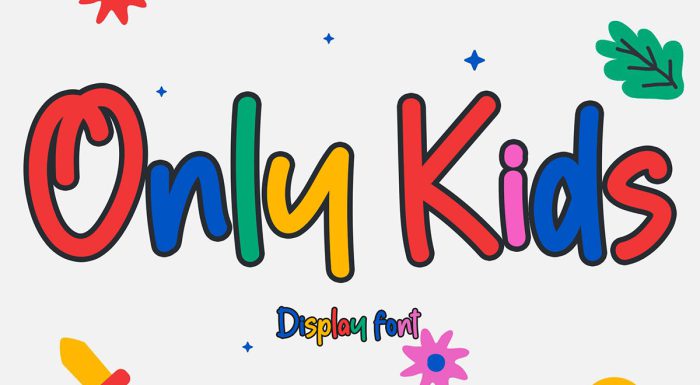
فونت Only Kids انگلیسی
| ⭐ توضیحات | فونت Only Kids Font را معرفی می کنیم، یک تایپ نمایشی بازیگوش و غریب که جوهره شادی و تخیل دوران کودکی را به تصویر می کشد. این فونت با حروف پر جنب و جوش و دوستانه خود، حس لذت بخشی را به طرح های شما می بخشد.
فونت Only Kids که برای کتابهای کودکان، پوسترها و پروژههای برندسازی بازیگوش ایدهآل است، حس سرگرمی و معصومیت را به ارمغان میآورد و تجربهای بصری ایجاد میکند که در قلب جوان و جوان طنینانداز میکند. |